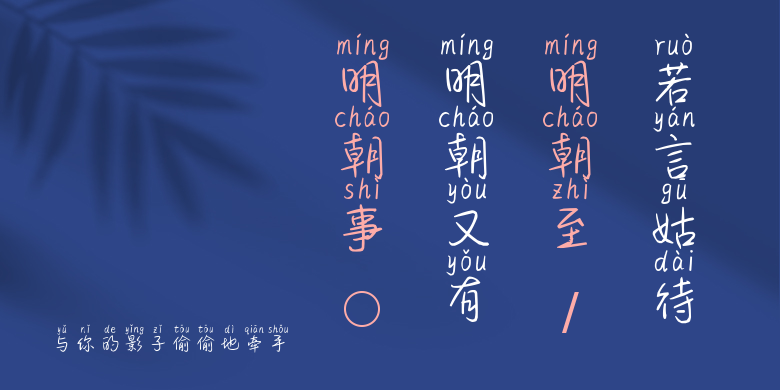
与你的影子偷偷地牵手
与你的影子偷偷地牵手,这款字体结构工整、笔画清晰,兼顾美观与易读性,适用于标题、正文、海报、包装、LOGO 等多种场景。字形优雅稳定,风格百搭耐看,适配日常排版与创意设计,让文字呈现更舒适、更具质感。与你的影子偷偷地牵手一笔一画,皆是细节,以均衡的比例、流畅的线条打造舒适视觉体验,字形端正大气,风格简约现代。无论是商业设计、品牌宣传还是日常排版,都能轻松驾驭,让文字更有格调与力量。与你的影子偷偷地牵手字体下载。